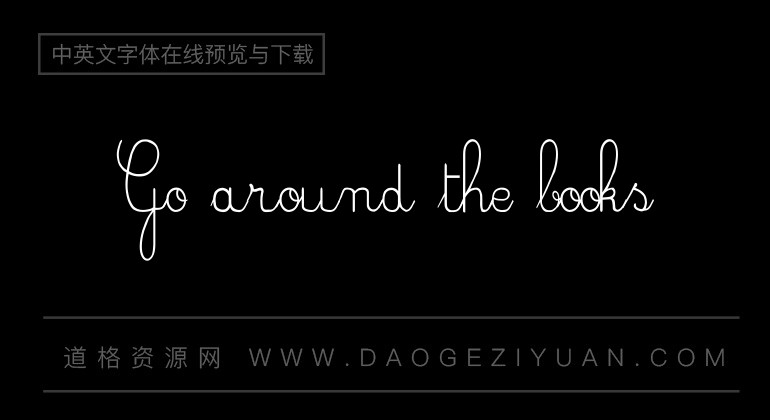
Go around the books
Go around the books 是一款字体,由荷兰设计师Koen van der Bliek设计,于2013年发行。该字体拥有简约的外观,更多的是以线条和折线为主,给人以清新的感觉。它的字体拥有独特的设计,可以用于创作多种不同风格的文字,从复古到现代,从传统到现代,都可以使用它来构建出完美的文字效果。
Go around the books是一款非常不错的手写艺术字体,具有很好的视觉感,适合于文化类的宣传设计、商业类品牌的广告和产品包装设计以及个性化文字排版等较多场景。